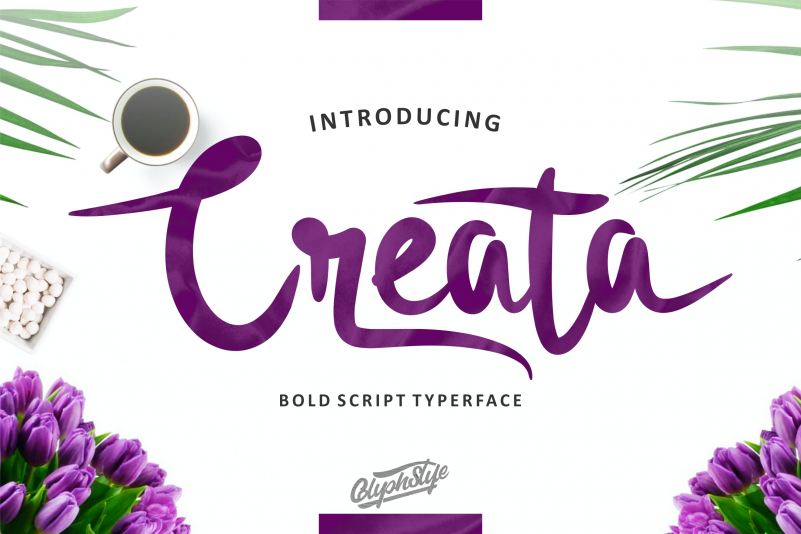
Creata Script Font – Fonte Grátis
Creata Script Font – Download Grátis
Creata Script Font
A fonte Creata Script é uma escolha perfeita para qualquer projeto que deseja dar um toque autêntico e elegante à sua tipografia. Originada no universo de tipos escritos a mão, essa fonte foi cuidadosamente criada pela designer GlyphStyle com uma técnica artesanal que resulta em letras fluidas e personalizadas. Perfeita para uso em designs de marca, cartões de convite ou publicações online, Creata Script oferece um estilo único e sofisticado que destaca seu conteúdo como nunca antes. Aproximadamente entre a elegância de uma fonte serifada e o charme não formal de uma fonte sans-serif, esta é uma excelente opção para quem busca adicionar um toque especial aos seus trabalhos visuais. Quer saber mais sobre como Criar Script Font? Para obter as últimas informações e dicas sobre esse tipo de font, acesse o nosso blog especializado em recursos gráficos. Você encontrará tutoriais úteis para criar e personalizar sua própria fonte escrita a mão, assim como dicas detalhadas para maximizar o impacto visual de seus projetos.